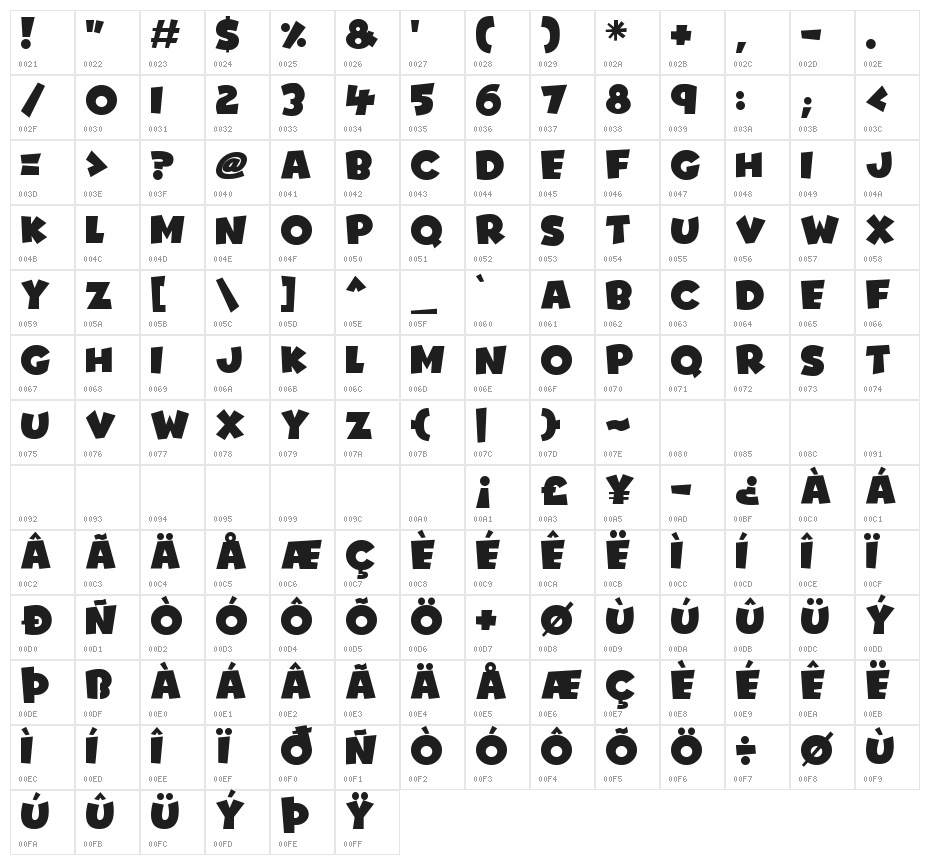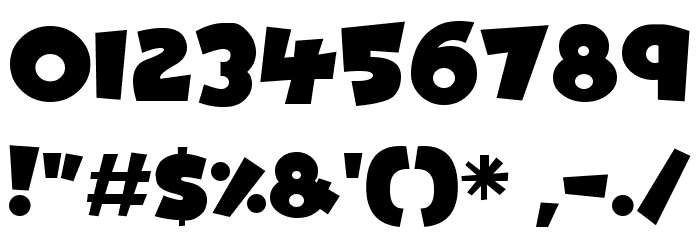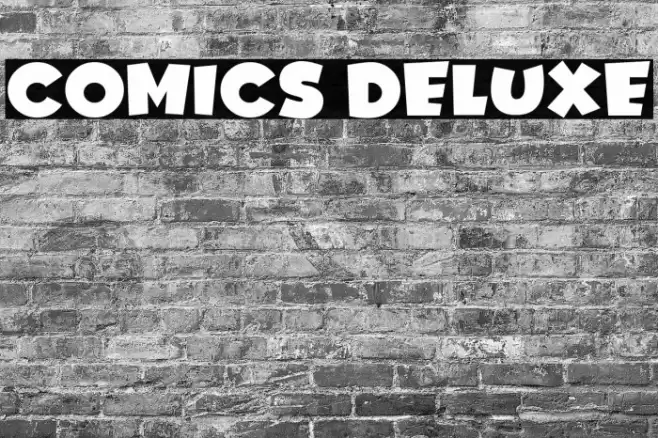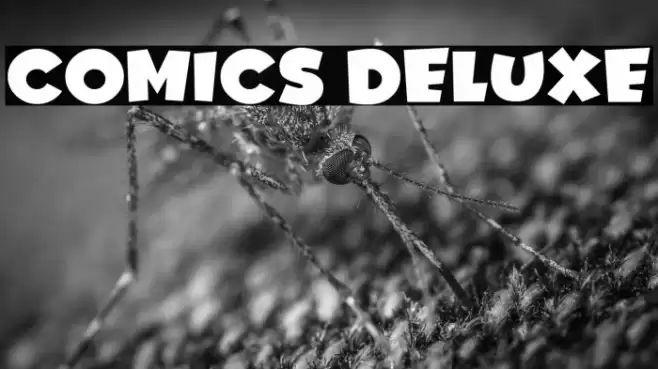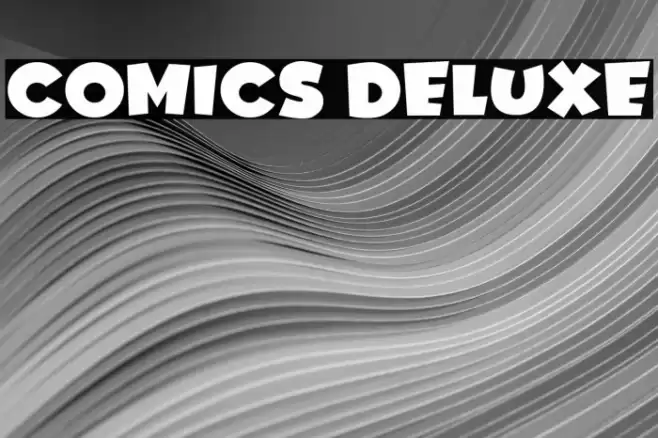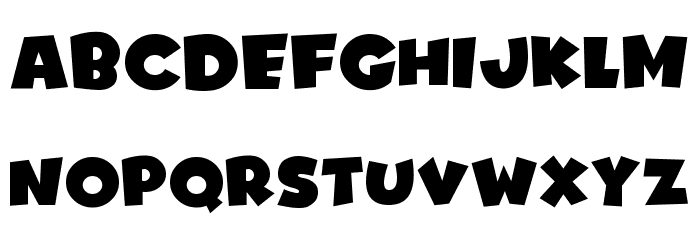
Comics Deluxe Font
| 全体的なスタイル | Playful, Cartoonish |
| おすすめプロジェクト | Ideal for comic books, children's books, playful branding, posters, and any design requiring a fun, informal touch. |